随着计算机时代的到来,字库已经成为人们工作生活的一部分,每天都会接触它、使用它。不同的风格应用于不同的领域,女性字体其实就是风格较于秀丽柔美的字体,字体一般优美清新、线条流畅,给人以华丽柔美之感。频繁使用于化妆品、饰品等主题的设计领域。下面这款图片字体就非常符合女性字体的特征。
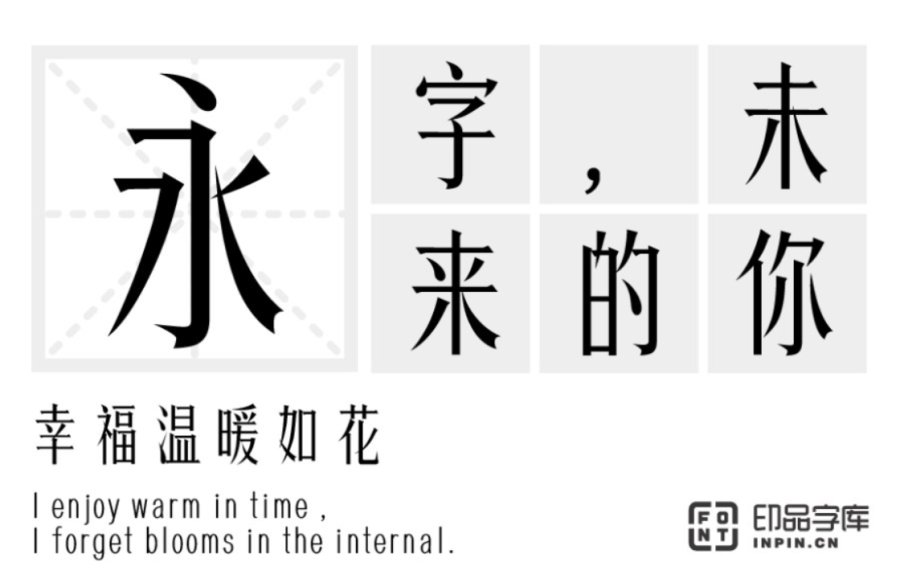
印品清秀体:这是一款气质娟秀,清雅悦目,个性鲜明的字体,字形工整秀长,细节飘逸。笔画更加纤细修长,整体看起来舒服易读,适用于带有清和雅致风格的标题和正文排版,logo设计、广告、印刷等领域。
印品雅宋简:这款字体线条流畅顺滑,平整耐看,棱角柔滑,装饰角的圆滑处理,使整款字体看起来既不缺少正式感又能增添个性,字体浑厚有力十分耐看,整体庄重,结实,端正大气,适用于标题,封面等场景。
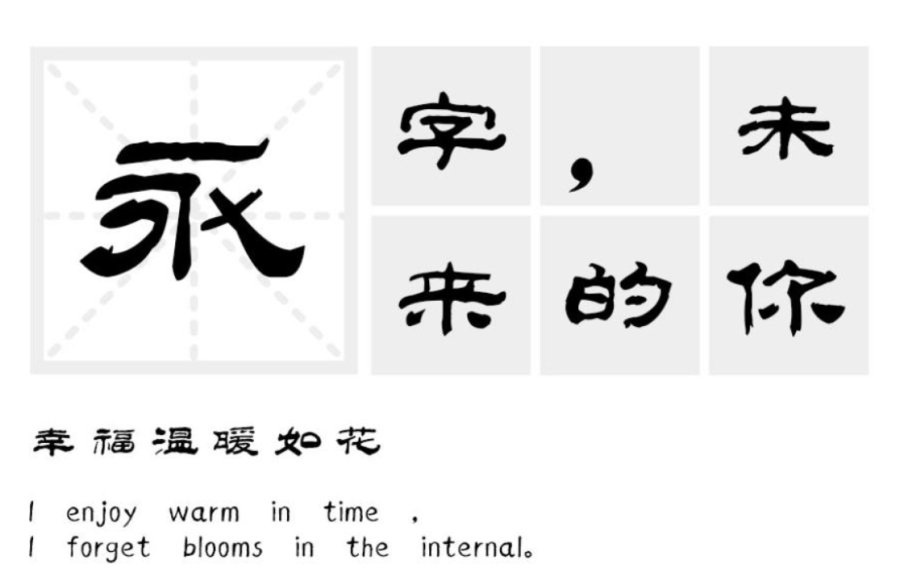
汉标丛台体:轻松活泼笔画,俏皮可爱的构字,组成了极具少女气息的女生风格。特别是一些转折处,采用大圆角的处理,配以俏皮的构字,将女生可爱的一面表现的淋漓尽致。适用于文艺类的书刊、品牌广告和产品包装设计,以及社交网络的个性化用字。